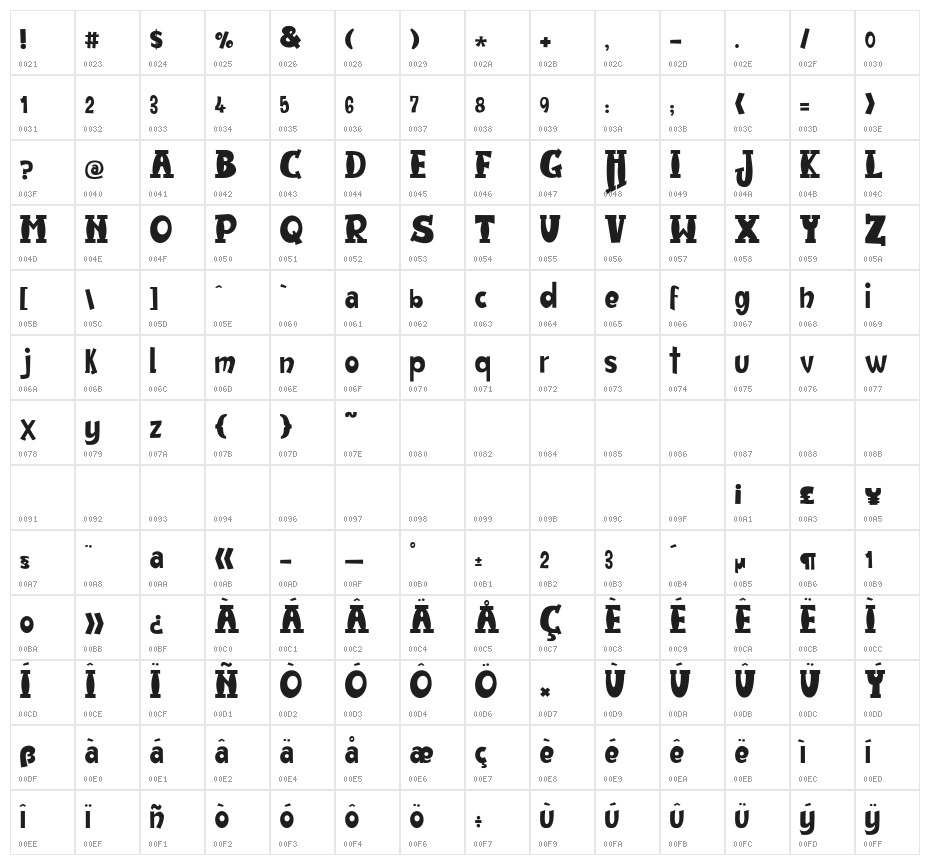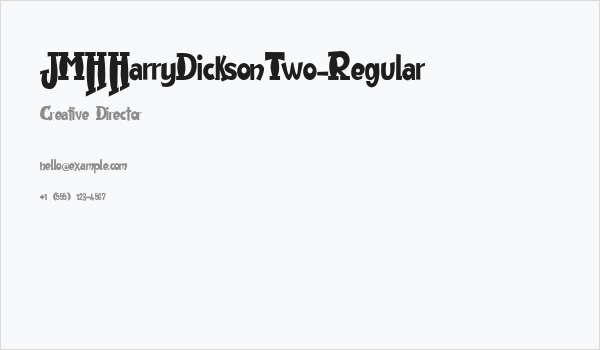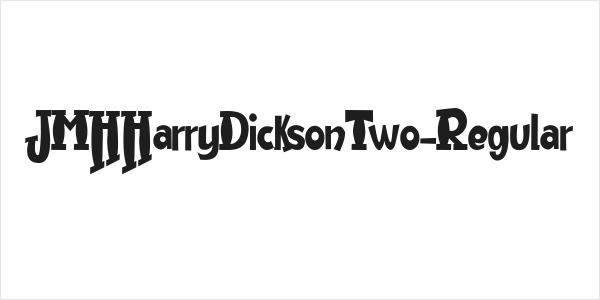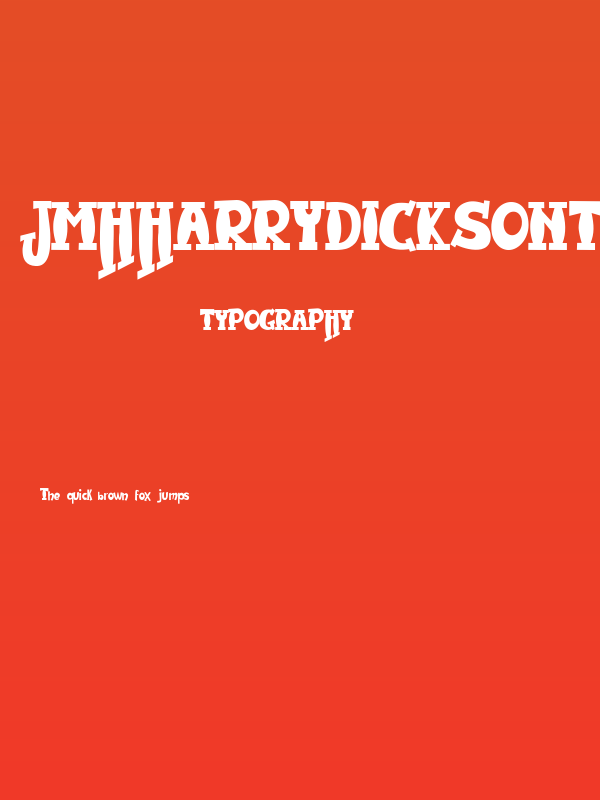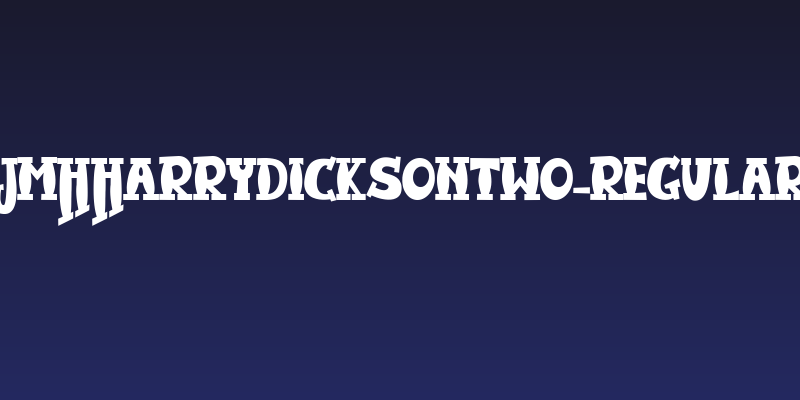
JMHHarryDicksonTwo-Regular Font
| Estilo general | Vintage |
| Proyectos propuestos | Ideal for retro-themed posters, playful branding, children's book covers, and eye-catching headlines. |